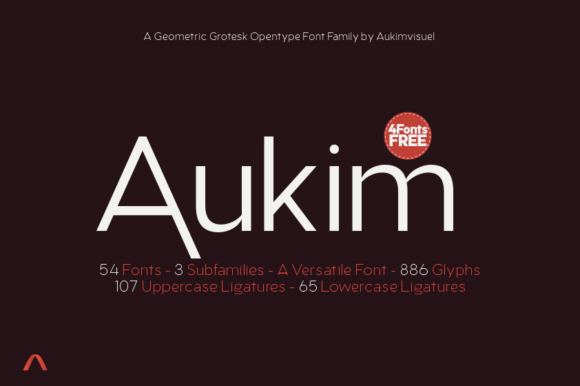
Aukim Free
Aukim Free: A Fonte Sans Serif Minimalista que Vai Transformar Seus Projetos
Se você está em busca de uma tipografia que combine minimalismo e versatilidade, Aukim Free é a escolha perfeita. Essa fonte sans serif foi desenvolvida para ser limpa, elegante e, acima de tudo, fácil de integrar a qualquer tipo de design, seja ele digital ou impresso.
Por que Aukim Free se destaca?
- Design Minimalista: Linhas simples e formas geométricas que garantem legibilidade em tamanhos pequenos e grande impacto visual em títulos.
- Compatibilidade Universal: Funciona perfeitamente em sites, aplicativos, logotipos, cartazes, embalagens e apresentações corporativas.
- Variedade de Pesos: Disponível em múltiplas espessuras, permitindo criar hierarquias tipográficas claras e atraentes.
- Suporte a Diferentes Idiomas: Inclui caracteres latinos, acentuados e símbolos essenciais para projetos em português.
Como Aukim Free pode melhorar seu workflow criativo
Incorporar Aukim Free ao seu arsenal de fontes traz benefícios imediatos:
- Rapidez na escolha da tipografia: Seu visual neutro combina com quase qualquer paleta de cores e estilo visual.
- Consistência visual: Use-a em títulos, subtítulos e corpo de texto para manter uma identidade coesa.